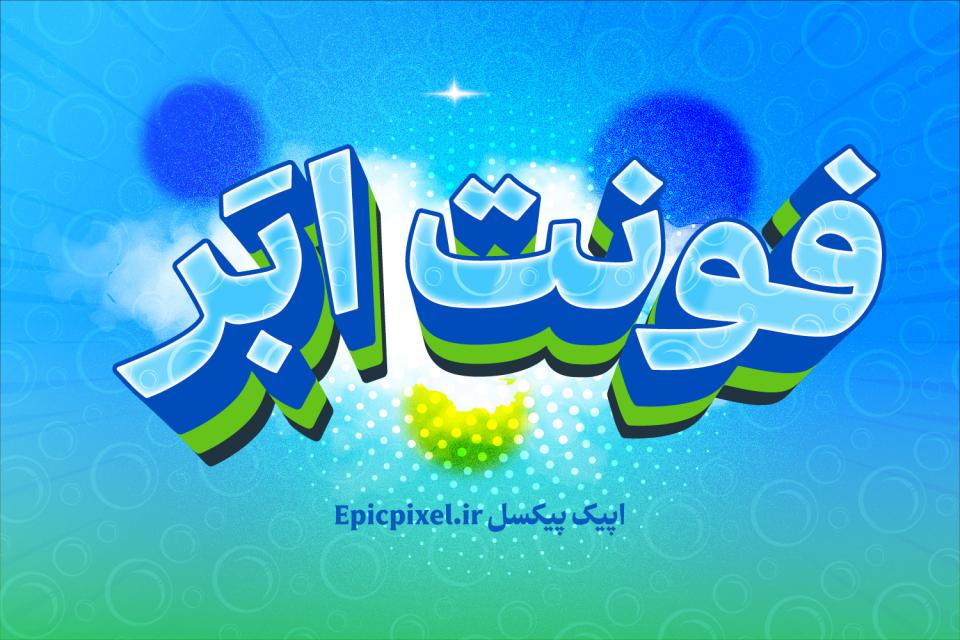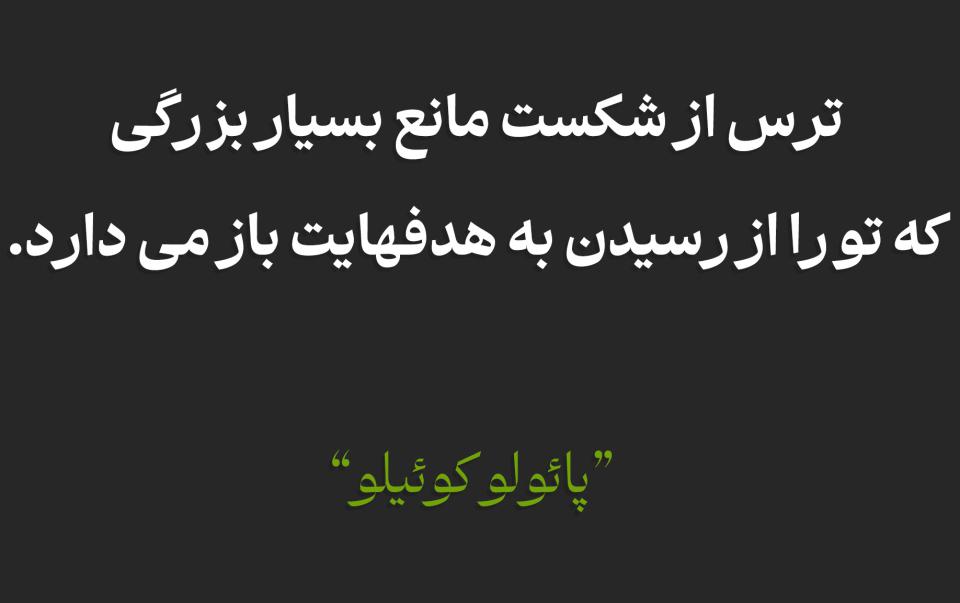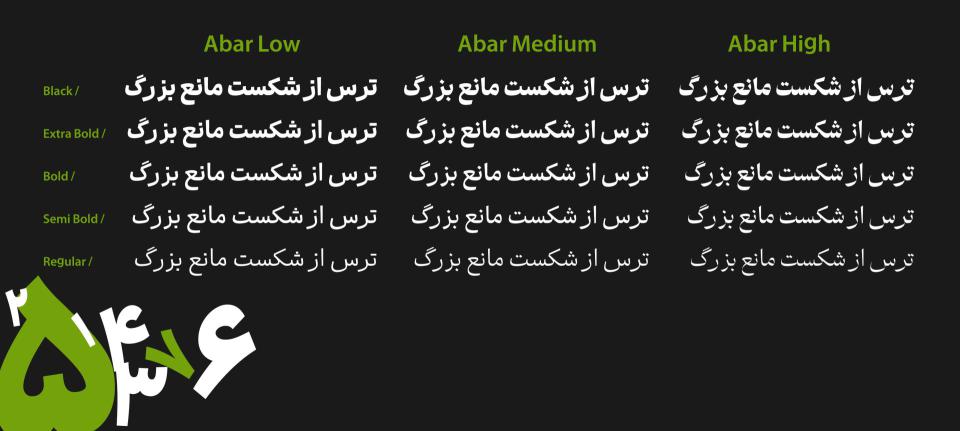
فونت ابر، با طراحی مدرن و خوانایی بالا، گزینه ای ایده آل برای متن های طولانی و عناوین جذاب است. این فونت با ۵ وزن مختلف (از Regular تا Black) و سه سبک مجزا (Low، Mid و High در نسخه حرفه ای)، انعطاف پذیری بالایی را در طراحی های گوناگون ارائه می دهد. اگرچه نسخه پایه آن رایگان است، اما برای دسترسی به تمام ویژگی ها مانند سبک های Mid و High و همچنین فرمت های وب فونت (woff) که برای استفاده در وب سایت ها ضروری هستند، نیاز به خرید نسخه کامل دارید.
یکی از ویژگی های برجسته فونت ابر، طراحی ظریف و در عین حال قدرتمند آن است که هم در متن های چاپی و هم در صفحات وب، جلوه ای حرفه ای به کار می بخشد. این فونت به خوبی برای متن های طولانی طراحی شده و خستگی چشم را کاهش می دهد. با این حال، تنوع سبک های آن در نسخه رایگان محدود است و برای پروژه هایی که نیاز به تنوع بیشتری دارند، ارتقاء به نسخه حرفه ای توصیه می شود. به طور خلاصه، فونت ابر با ارائه ترکیبی از زیبایی و کارایی، انتخابی مناسب برای طراحان و نویسندگانی است که به دنبال فونتی مدرن و خوانا هستند.
یکی دیگر از مزایای این فونت، پشتیبانی از فرمتهای مختلف مانند TTF، OTF، WOFF و WOFF2 است که تضمین میکند در پلتفرمهای گوناگون از وبسایتها گرفته تا نرمافزارهای گرافیکی، بدون مشکل اجرا شود. این ویژگی به خصوص برای طراحان وب که به دنبال فونتی سازگار با مرورگرهای مختلف هستند، بسیار حائز اهمیت است. همچنین، ابر دارای نسخهای ویژه با اعداد کاملاً فارسی است که به زیبایی و یکپارچگی متنهای فارسی کمک میکند.